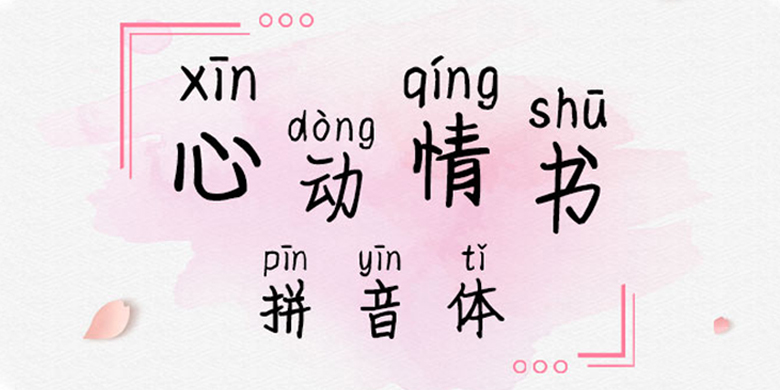
方正手迹-心动情书拼音体
字体品牌: 方正手迹 设计师:余丹 字体分类:常规书写·硬笔 字体属性:精品字 字符集:大陆简体(GB2312-80) 发布时间: 2020
该字为心动情书体加拼音,汉字部分有较好的阅读效果,拼音部分的字母有比较大的字面,这样的拼音体具有良好的识别性。适用于文艺类的书刊、品牌广告和产品包装设计,以及社交网络的个性化用字。